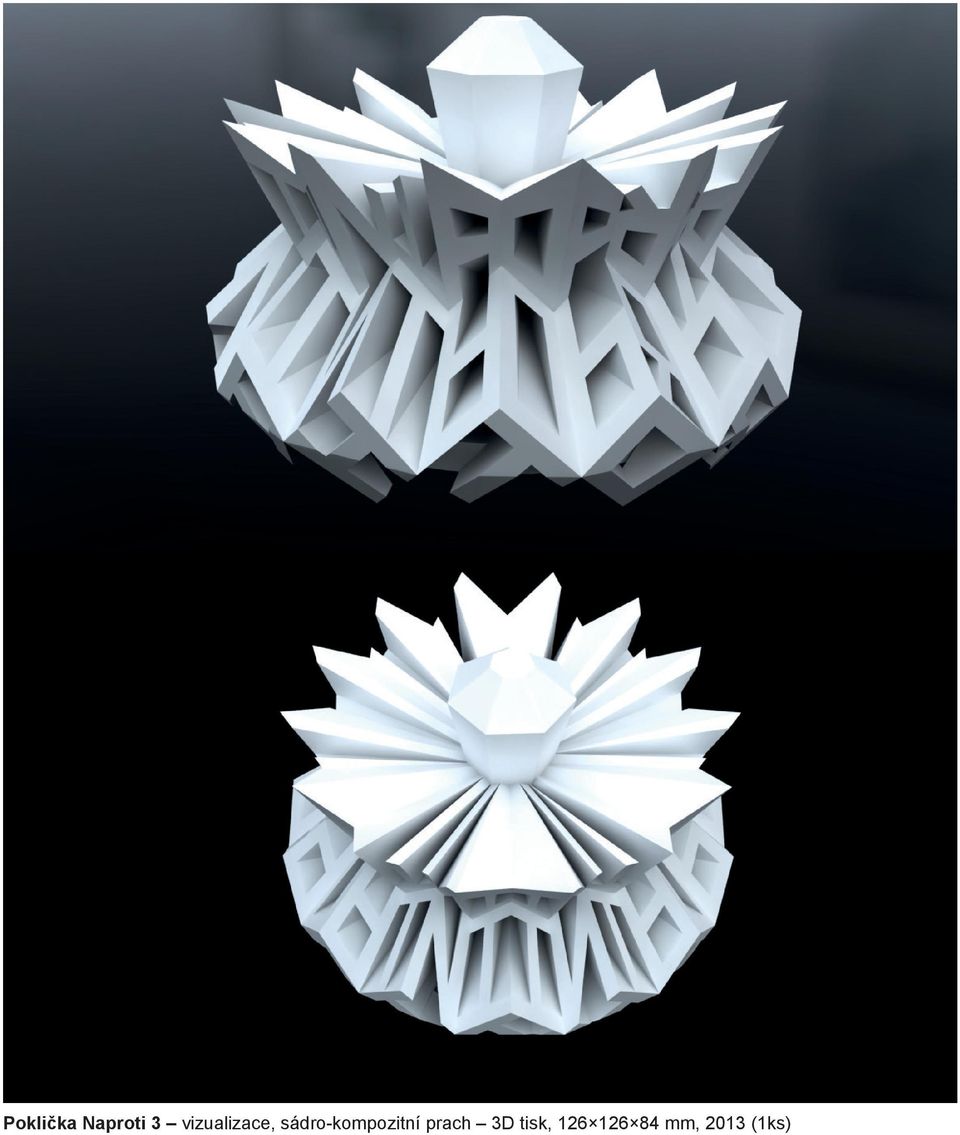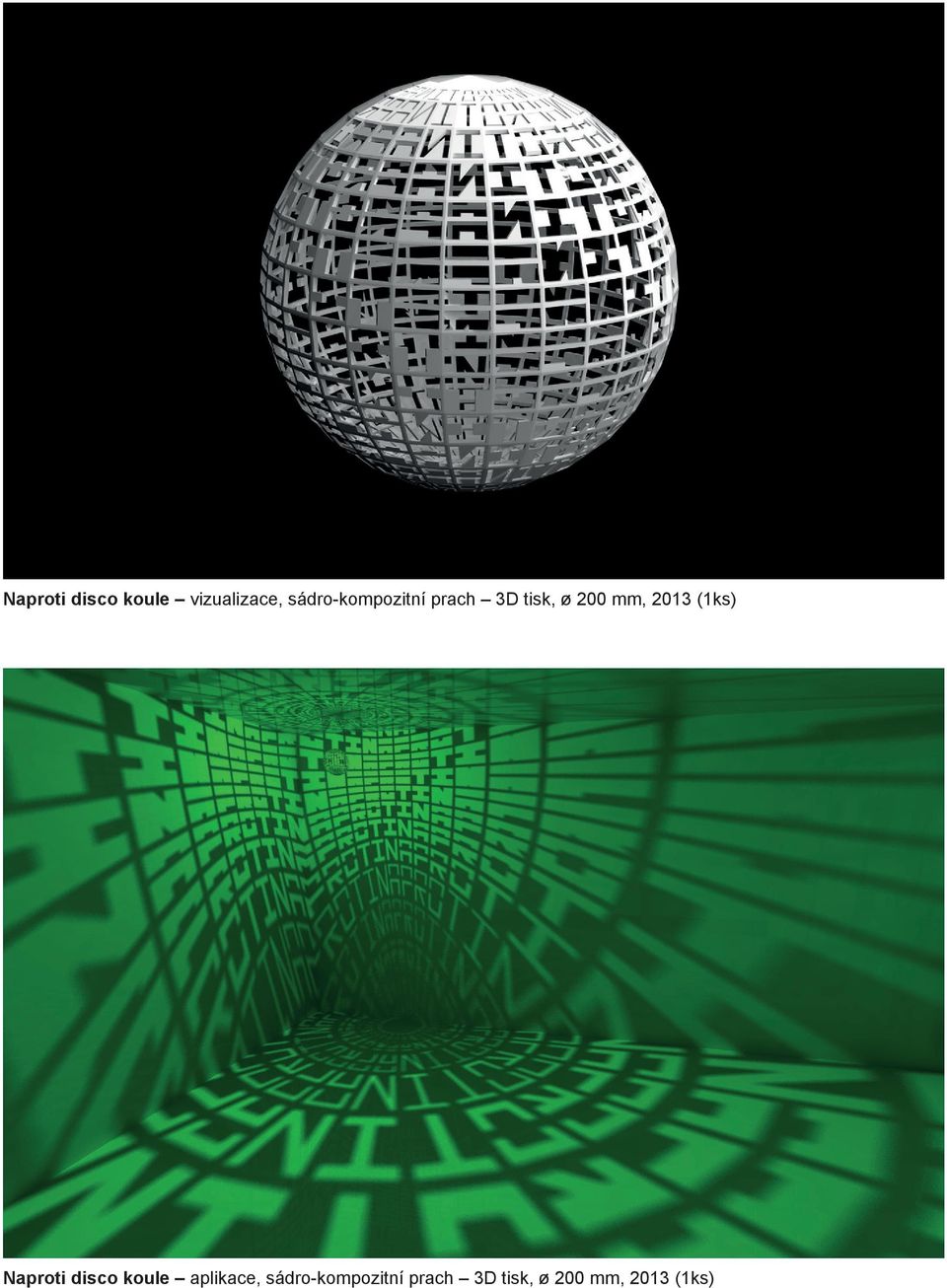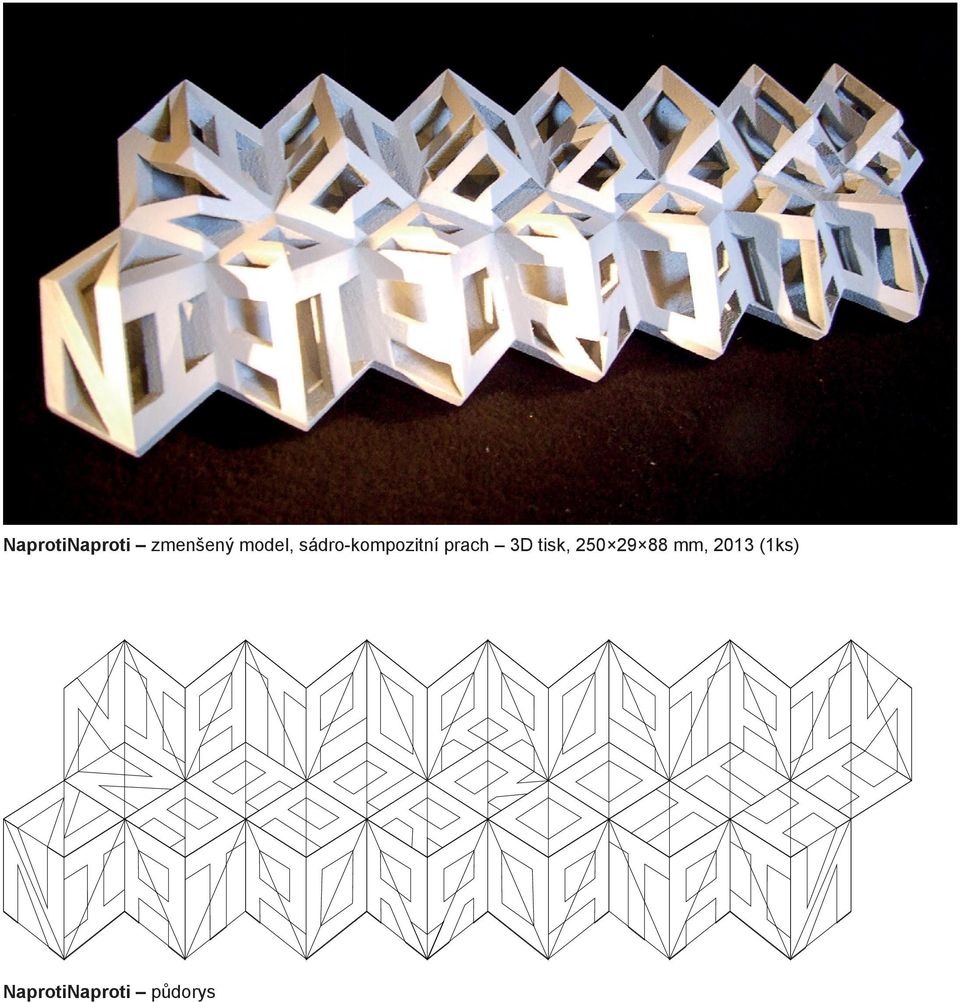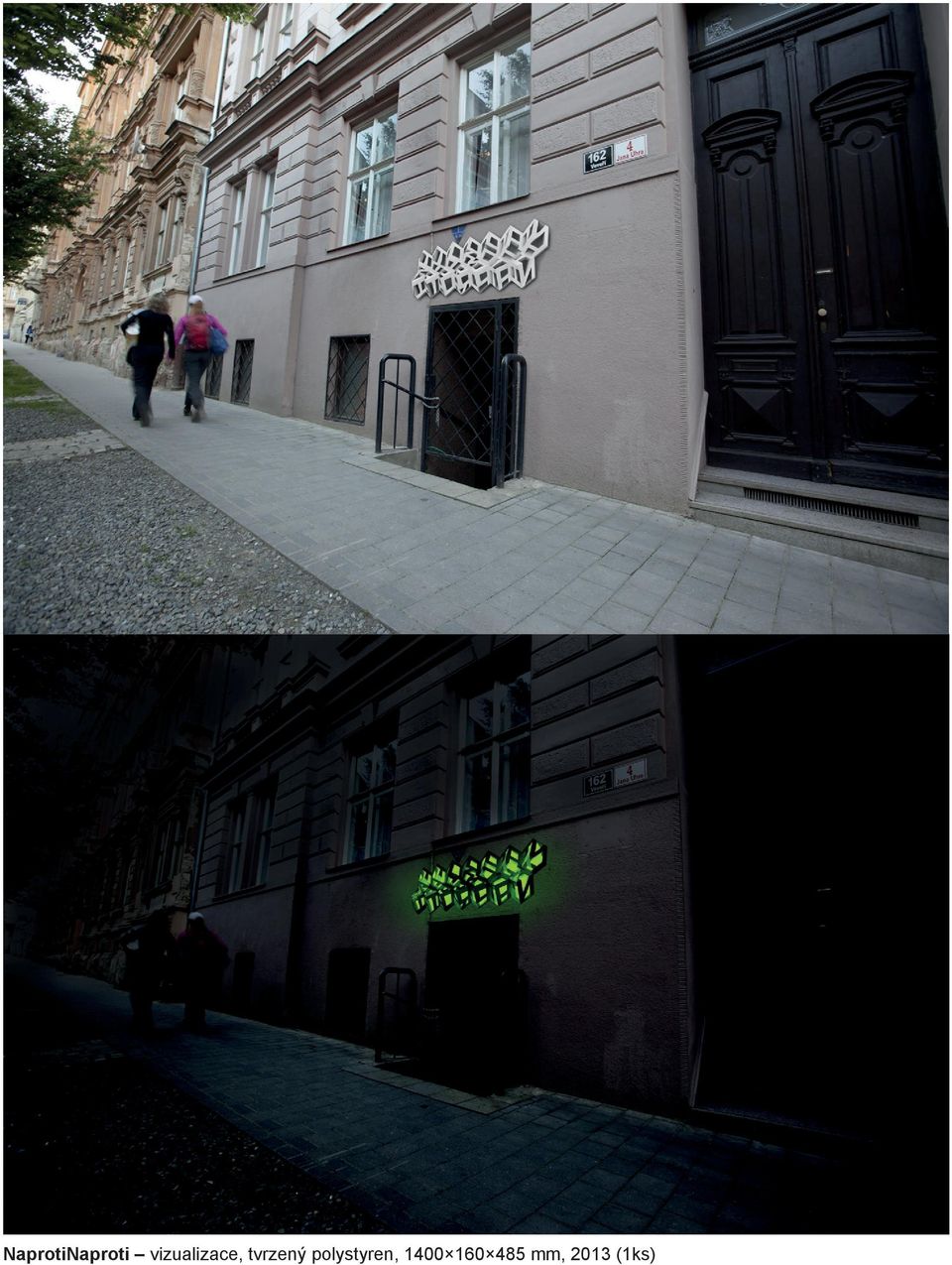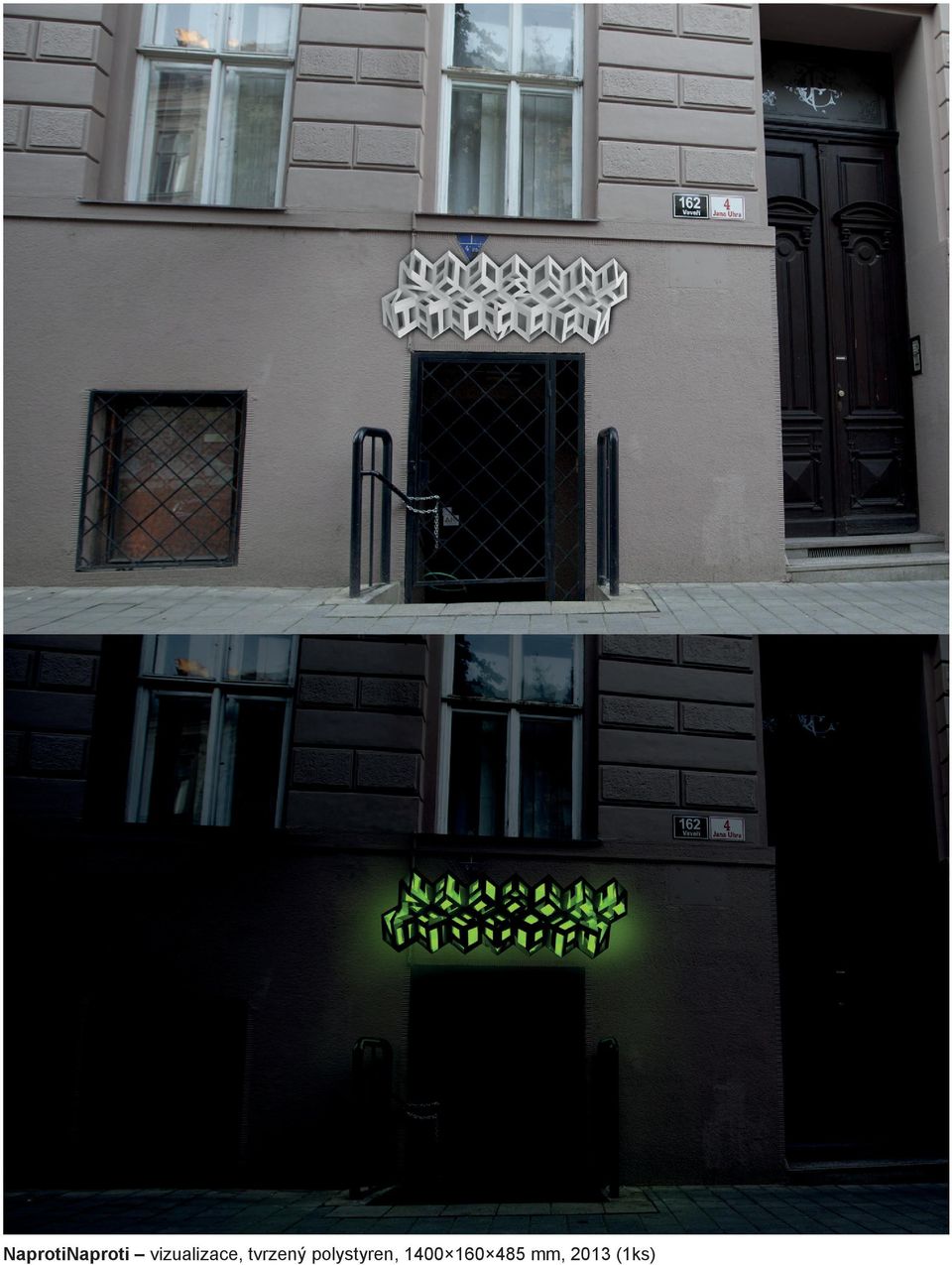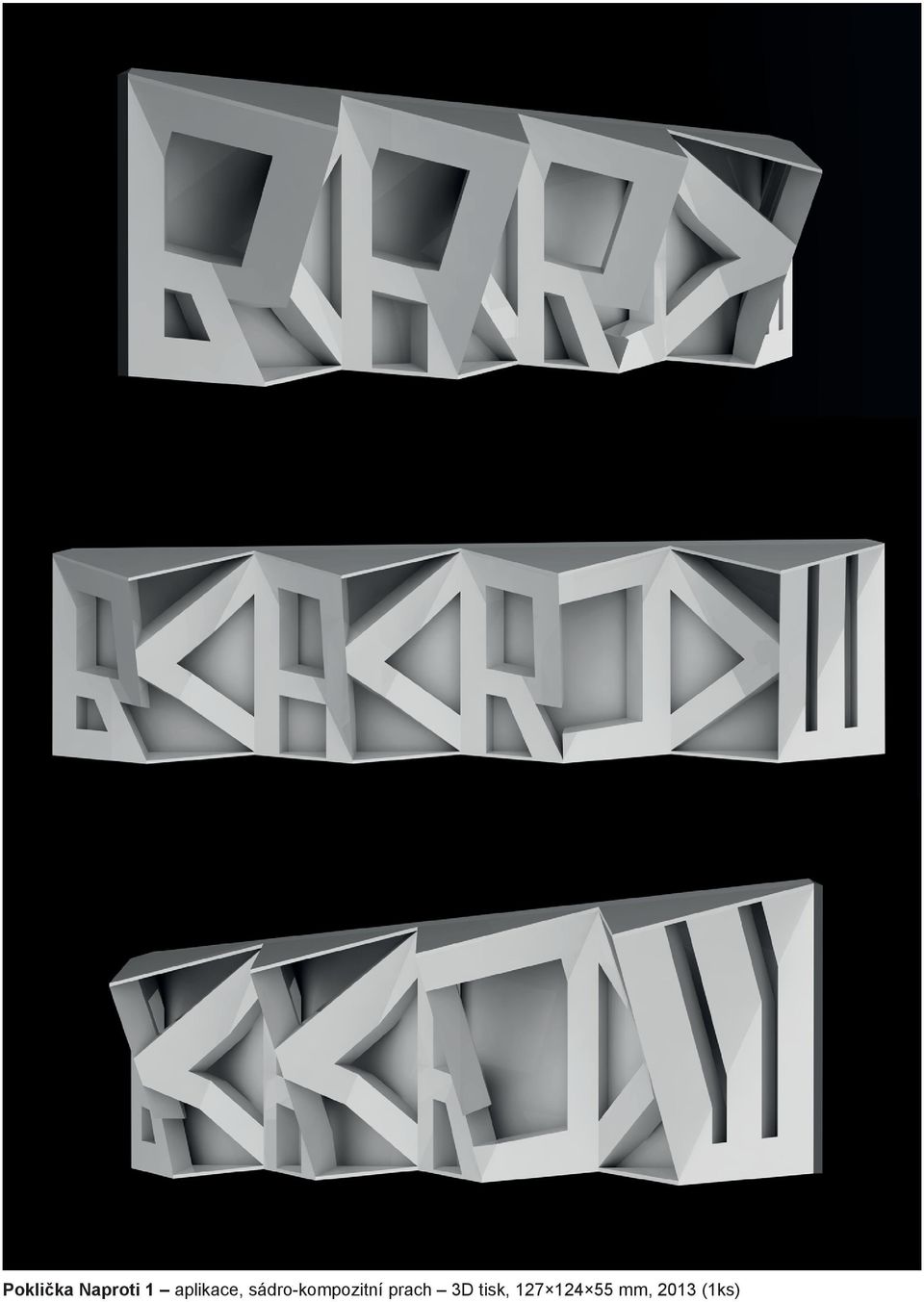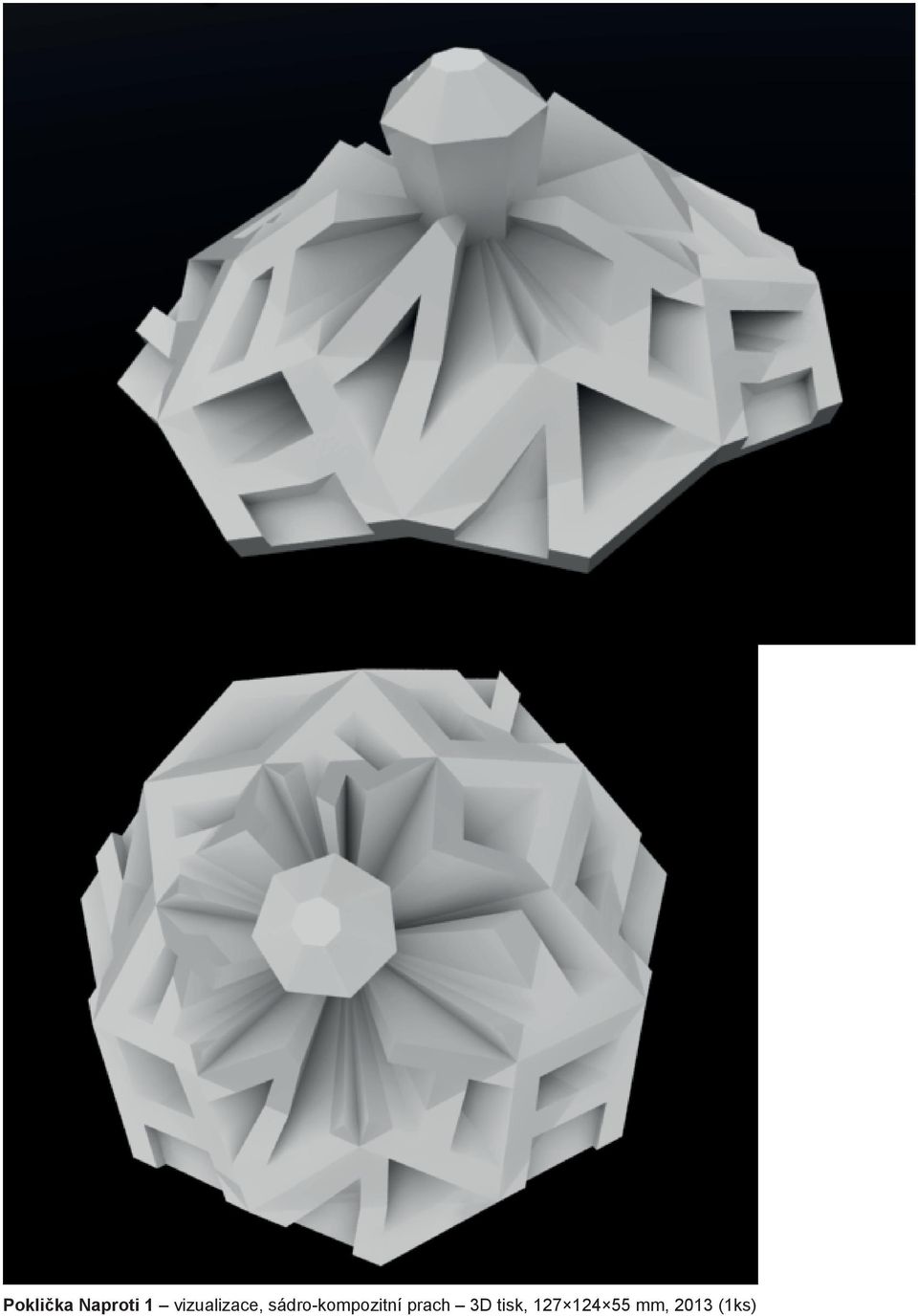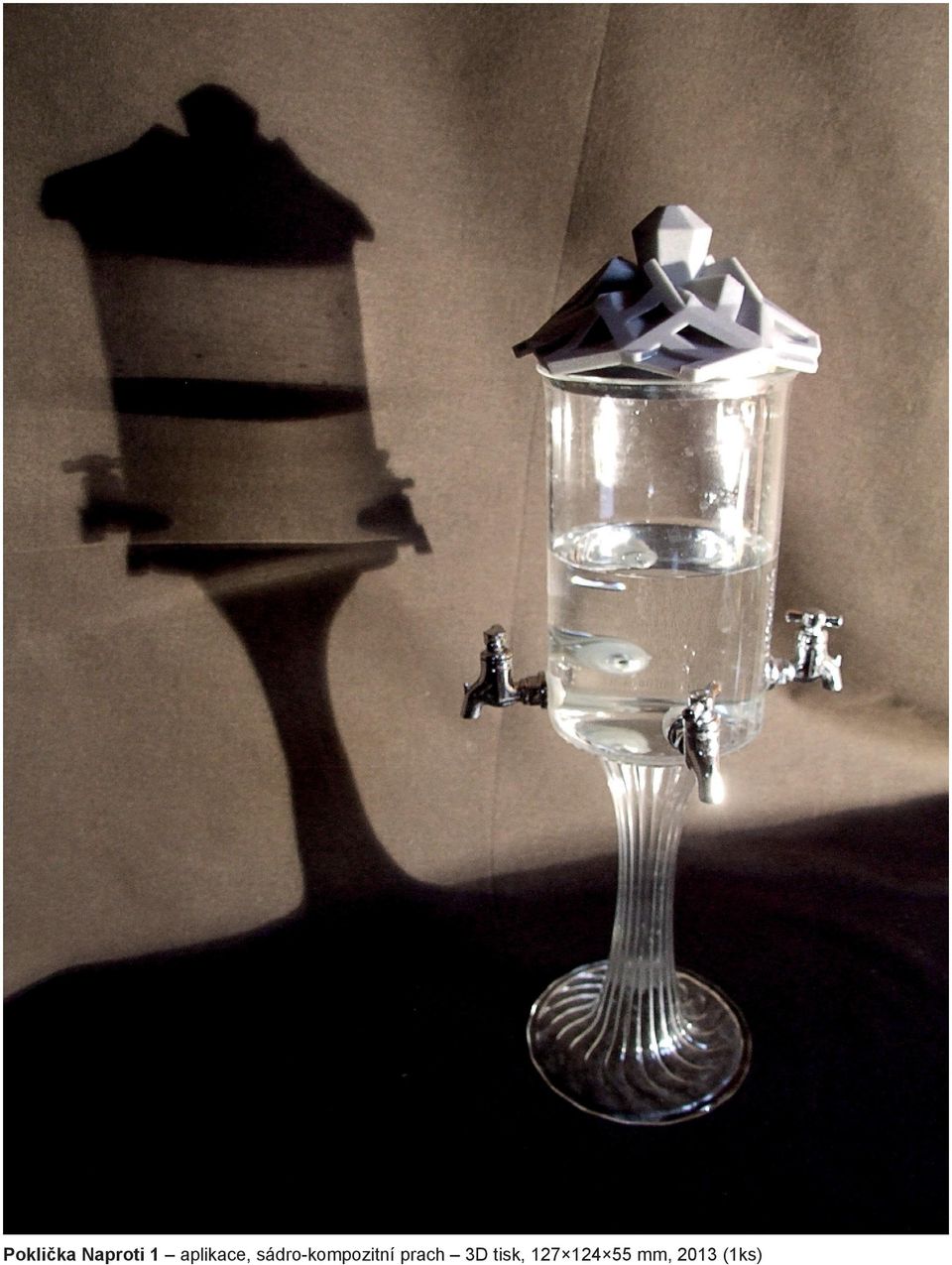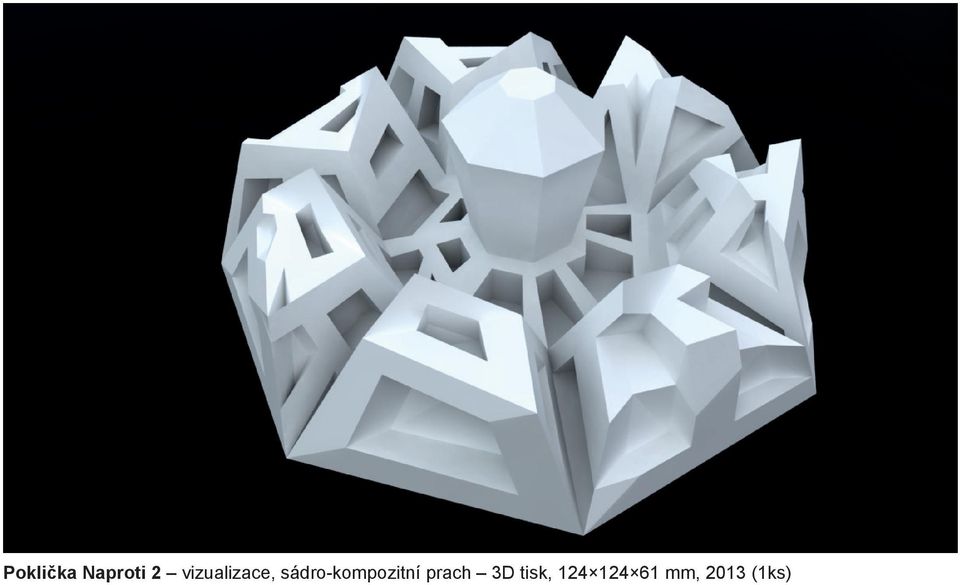
2 NaprotiNaproti zmenšený model, sádro-kompozitní prach 3D tisk, mm, 2013 (1ks) NaprotiNaproti půdorys
3 NaprotiNaproti vizualizace, tvrzený polystyren, mm, 2013 (1ks)
4 NaprotiNaproti vizualizace, tvrzený polystyren, mm, 2013 (1ks)
5 Poklička Naproti 1 aplikace, sádro-kompozitní prach 3D tisk, mm, 2013 (1ks)
6 Poklička Naproti 1 vizualizace, sádro-kompozitní prach 3D tisk, mm, 2013 (1ks)
7 Poklička Naproti 1 aplikace, sádro-kompozitní prach 3D tisk, mm, 2013 (1ks)
8 Poklička Naproti 2 vizualizace, sádro-kompozitní prach 3D tisk, mm, 2013 (1ks)
9 Poklička Naproti 2 aplikace, sádro-kompozitní prach 3D tisk, mm, 2013 (1ks)
10 Poklička Naproti 3 vizualizace, sádro-kompozitní prach 3D tisk, mm, 2013 (1ks)
11 Naproti disco koule vizualizace, sádro-kompozitní prach 3D tisk, ø 200 mm, 2013 (1ks) Naproti disco koule aplikace, sádro-kompozitní prach 3D tisk, ø 200 mm, 2013 (1ks)
12 Ve veřejném prostoru se setkáváme s různými způsoby zacházení s typografií k propagačním aj. účelům. Povětšinou se jedná o velkoplošné tisky, v případě náročnějšího zadavatele o trojrozměrné litery různých barev a povrchů, které jsou zpravidla pouze extrudovány a více či méně odsazeny od různých podkladů. Takovéto 3D objekty jistě zaujmou více, než plošné. Proto jsem si za cíl stanovil vytvořit objekty vizuálně poutavější, které splní funkci nositele informace a zároveň se v reálném prostředí pokusí překročit běžné formy sdělení a přizbůsobí se konkrétnímu prostoru a užití. Pro svůj projekt jsem si vybral Absint bar s názvem Naproti, který vlastní moji přátelé a nachází se blízko Konečného náměstí v Brně. Podnik vyniká rozmanitou nabídkou nápojů s obsahem různých jedů, jejichž konzumace je blízce spjata s uměleckou a intelektuální bohémou od 18. století dodnes. Tento bar se stále rozšiřuje a s ním i jeho rozmanitá klientela nejen vyznavačů psychedelie. Proto nastala možnost inovovat výzdobu v rámci mnou zvoleného tématu. Psychedelickou mnohopohledovost na realitu jsem se snažil promítnout do užitných objektů dekorativního charakteru. Nesou t extovou informaci, ve smyslu morfózy tvarů písmen a jsou čitelné z různých úhlů pohledu i pozic pozorovatele. Všechny objekty jsou vytvořeny na základě geometricky konstruovaných variant sedmiúhelníku, sedmicípých hvězdic a jejich vztahů, vycházejících z počtu písmen v názvu podniku. Tvoří čtyřúhelníkové plochy, do kterých jsou zasazovány modulárně vytvořené litery Naproti. Toto jsem se pokusil shrnout do objektu, se kterým by se potencionální návštěvník setkal jako s prvním NaprotiNaproti, který má sloužit jako vývěsní štít. Byl by vyroben z tvrzeného polystyrenu a umístěn na fasádě nad vstupními dveřmi v úrovni očí dospělého člověka. Dal by kolemjdoucímu možnost rozeznávat a prohlížet si ten samý nápis ze všech možných pozic. Při chůzi kolem by objekt upoutal pozornost i méně vnímavé osoby bez ohledu na její výšku, pozici nebo schopnosti rozumět textu, díky prostorovému uzpůsobení. Je to komunikce na jiné úrovni, než je běžné a vývěsní štít by tak poukazoval na vyhraněnost podniku. Vše by bylo podpořeno zelenými LED diodami, navazujícími na vnitřní osvětlení podniku, umístěnými uvnitř jednotlivých písmen, pro vytvoření kontrastu, poutavosti a rozpoznatelnosti textu. Na vývěsní štít navazuje sada užitých předmětů v interiéru, což spolu vytváří malý jednotný vizuální styl. Navigační systém Naproti využívá principu schopnosti objektu sdělit z různých stran jinou informaci. V praxi by byly použity 3D tisky směrovky, umístěné na zdech interiéru, dávající kolemjdoucímu informaci v závislosti na jeho pozici. Jednou z dominant vybavení baru jsou tzv. absinthové fontány dekorativní skleněné stolní nádrže na ledovou vodu, podávané se sklenicí absinthu. Součástí fontány je skleněné víčko, které se při manipulaci často zničí. Proto jsem se rozhodl navrhnout 3D tisková náhradní víčka, které mají mohutnější madlo. Na geometricky vymodelovaném plášti hvězdicového půdorysu uplatňuji stejný princip práce s písmem jako u předchozích objektů, s rozdílem přidání více úhlů pohledu. Posledním objektem je parafráze na disco kouli Naproti disco koule, kde je písmo odečteno z pláště koule. Světelný zdroj uvnitř pohybující se koule, umístěné na stropu místnosti, vytvoří nepravidelnou projekci opakujícího se textu Naproti na stěny. Text ve 14 řadách a 28 sloupcích je možné číst v různých silách duktu verikálně i horizontálně. Testováním jsem zjistil, že všechny tyto objekty mohou působit na diváka jako pouhé dekorativní předměty a až po delším pozorování zjišťují textovou informační funkci, což bylo původním cílem vytvořit objekty vizuálně poutavé, s nástavbou textové informace. Domívám se, že objevené principy mají potenciál pro další práci, avšak časová a finanční náročnost užitých technologií proces komplikuje.